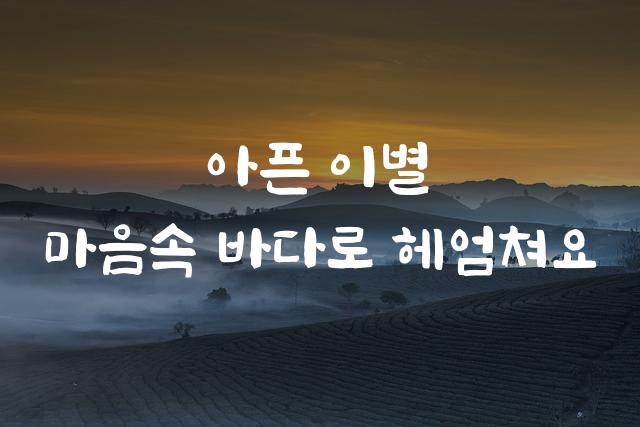
완도청정바다체는 제목용으로 디자인된 굴린 고딕 스타일의 한국어 폰트입니다. 깔끔하게 끊어진 선의 특징이 감각적인 디자인을 완성합니다.
기본 고딕, 길고/크고 계열의 생김새를 가지고 있으며
교육 자료, 인사말 카드, 카페 메뉴 등에서 자주 활용되며, 효과적인 메시지 전달에 적합합니다.
이 폰트는 음식/식음료, 라이프스타일, 관광/여행 분야에 잘 어울리며,
친근한, 편안한, 자연스러운 느낌을 담고 있는 것이 특징입니다.